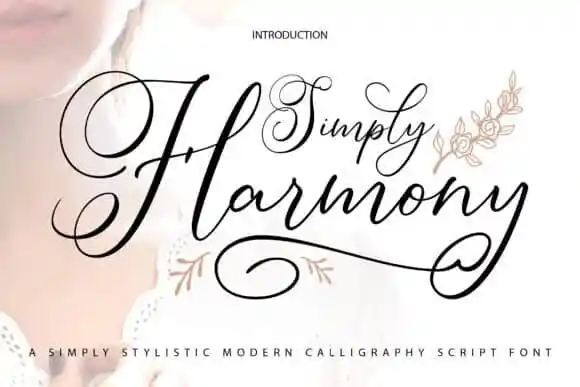
Simply Harmony Calligraphy Font
A Simply Harmony Calligraphy Font é uma elegante e artística tipografia à mão-dura que torna qualquer projeto de design em uma verdadeira estrela. O seu formato curvilíneo, cheio de suaves contornos, cria um ar romântico irresistível, perfeito para projetos requintados. Esta fonte é ideal para a criação de eventos formais com elementos clássicos, perfeita para casamentos em revistas, capas de livros e cartões de apreciação. A sua versatilidade é impressionante: pode ser usada em logotipos, identidades corporativas, cards de visita e até mesmo certificados. Seja você um designer de eventos, gráficos ou de qualquer área que exija uma aparência clássica, formal ou sofisticada, a Simply Harmony Calligraphy Font é definitivamente o ponto final para seus projetos.